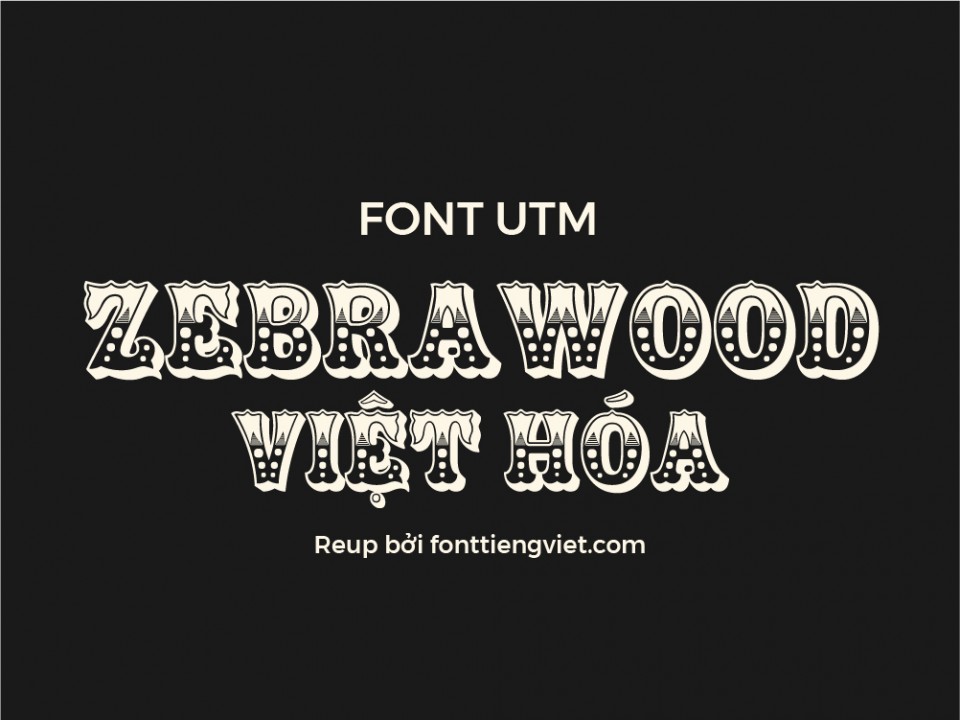
Giới thiệu về Font việt hóa UTM Zebrawood
Trong thế giới đồ họa, việc lựa chọn một bộ Font Miễn Phí phù hợp là yếu tố then chốt để tạo nên linh hồn cho tác phẩm. Font việt hóa UTM Zebrawood nổi lên như một lựa chọn hoàn hảo cho những ai yêu thích phong cách cổ điển, mạnh mẽ và đầy cá tính. Đây là phiên bản được tối ưu hóa bảng mã để các nhà thiết kế tại Việt Nam có thể dễ dàng sử dụng tiếng Việt có dấu mà không lo lỗi hiển thị.
Đặc điểm nổi bật của Font việt hóa UTM Zebrawood
Phong cách Typography độc đáo
Được lấy cảm hứng từ những mẫu chữ phương Tây thế kỷ 19, Font việt hóa UTM Zebrawood sở hữu những đường nét trang trí tinh xảo với các sọc dọc đặc trưng. Kiểu chữ này mang lại cảm giác hoài cổ của các gánh xiếc xưa hoặc những biển hiệu quảng cáo tại các thị trấn miền Tây. Nhờ cấu trúc chữ in hoa mạnh mẽ, nó rất phù hợp để làm tiêu đề bài viết, thiết kế bìa sách hoặc poster sự kiện.
Tính ứng dụng cao trong thiết kế
Dù mang hơi hướng cổ điển, nhưng khi áp dụng vào các dự án hiện đại như thiết kế logo hay thiệp mời, bộ font này vẫn giữ được sức hút riêng biệt. Độ tương phản cao giữa các nét chữ giúp thông điệp của bạn trở nên nổi bật và thu hút thị giác ngay lập tức. Các giáo viên và học sinh cũng có thể dùng font này để làm sinh động các bài thuyết trình hoặc dự án học tập sáng tạo.